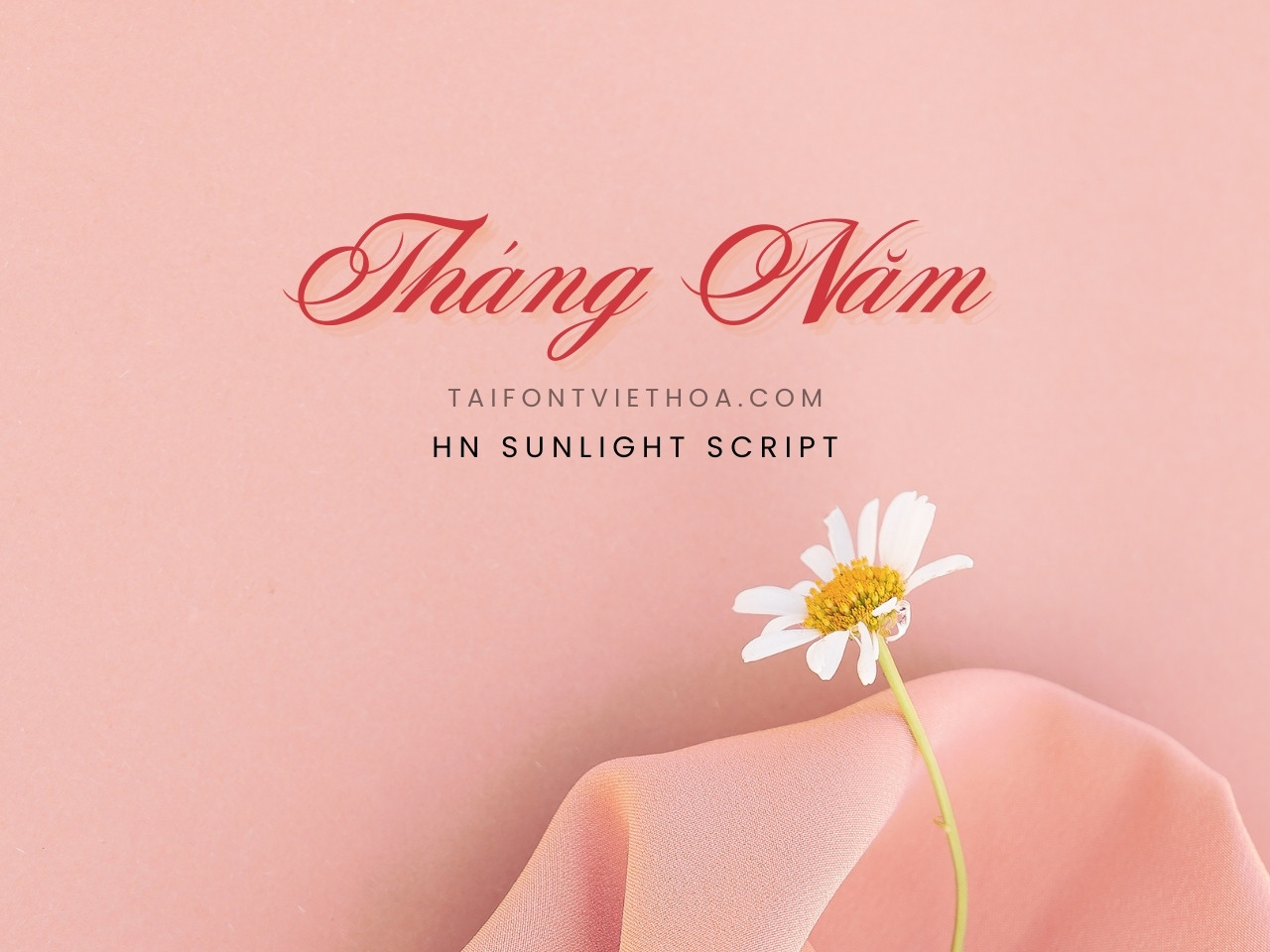
Font việt hóa Sunlight Script
Giới thiệu về font Sunlight Script
Sunlight Script là một font chữ viết tay mềm mại và thanh lịch, được thiết kế theo phong cách calligraphy hiện đại. Font mang lại cảm giác nhẹ nhàng, tinh tế nhưng vẫn giữ được sự cá tính cần thiết trong các thiết kế mang yếu tố cá nhân hóa. Phiên bản Việt hóa được thực hiện bởi Huy Nam, hỗ trợ đầy đủ tiếng Việt với hệ dấu sắc nét và các ký tự được tinh chỉnh cẩn thận. Ngoài tiếng Việt, font còn hỗ trợ hơn 40 ngôn ngữ khác thông qua bảng mã Latin và Latin Extended. Font Sunlight Script đã được taifontviethoa.com tuyển chọn và ứng dụng thực tế trong nhiều dự án thiết kế thiệp, logo và mỹ phẩm tại Việt Nam.
Đặc điểm thiết kế và ứng dụng của Sunlight Script
Sunlight Script sở hữu nét chữ bay bổng, mềm mại, có độ nghiêng nhẹ và liền mạch tạo cảm giác như viết bằng bút lông trên nền giấy cao cấp. Các ligatures được thiết kế kỹ lưỡng nhằm tăng độ liền mạch giữa các ký tự, tạo nên hiệu ứng thị giác thanh lịch và cá nhân hóa. Font phù hợp cho các thiết kế mang phong cách tinh tế, nữ tính hoặc lãng mạn.
Font này lý tưởng cho các ứng dụng như thiệp cưới, logo mỹ phẩm, bao bì sản phẩm làm đẹp, tiêu đề blog thời trang, hoặc các nội dung mạng xã hội hướng tới đối tượng nữ. Ngành nghề phù hợp gồm: wedding planner, mỹ phẩm, spa, thiết kế thời trang, nội dung lifestyle và sáng tạo nghệ thuật.